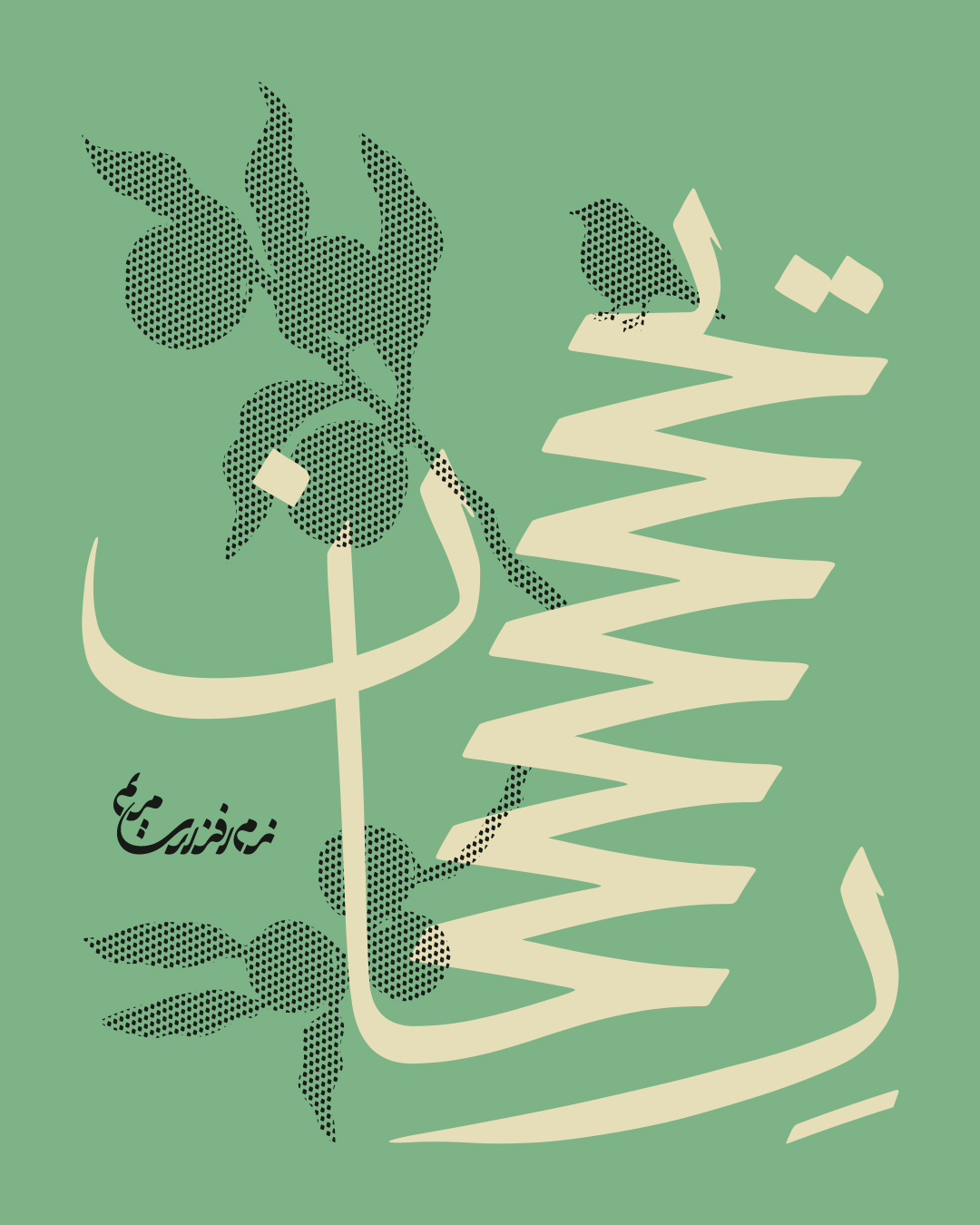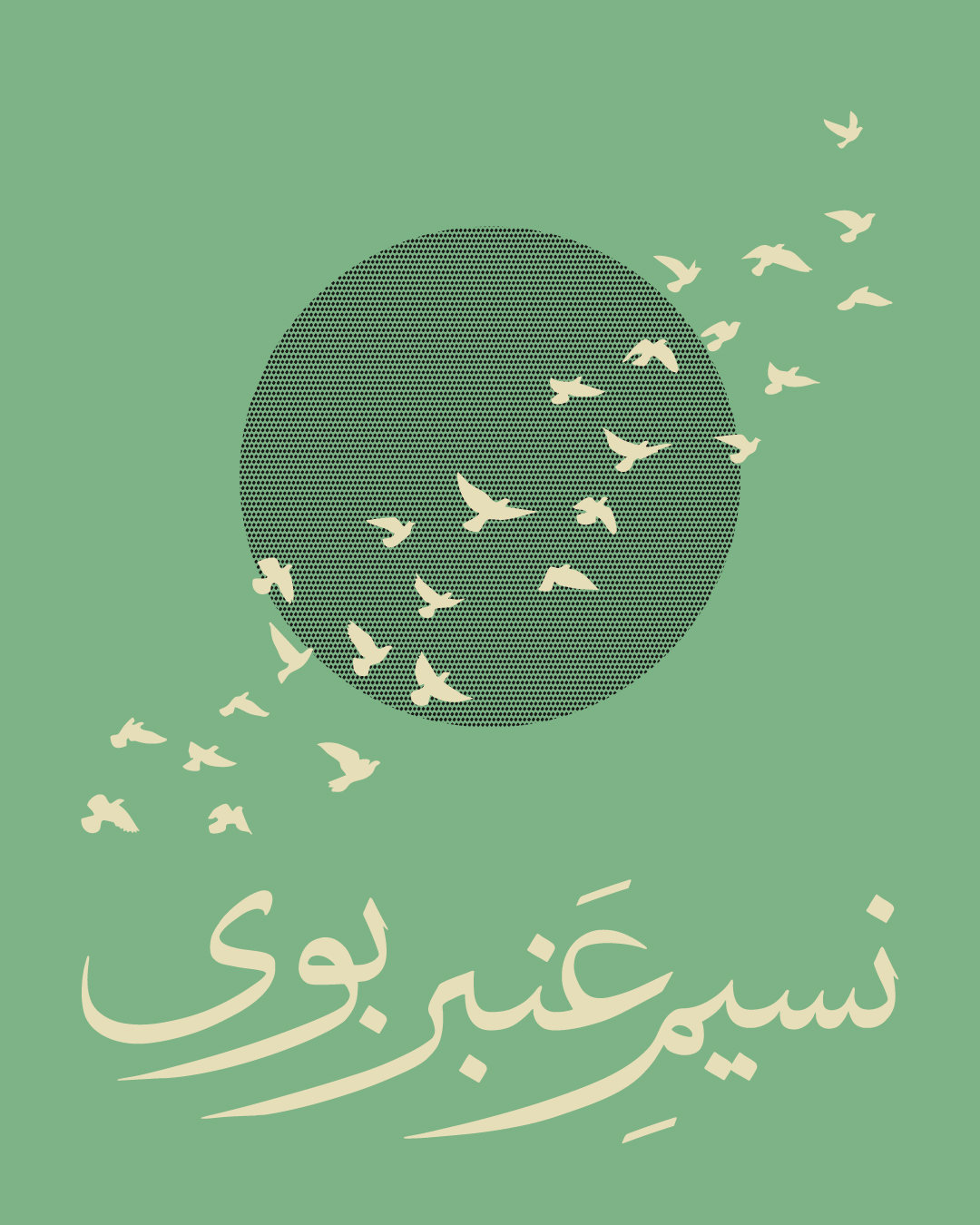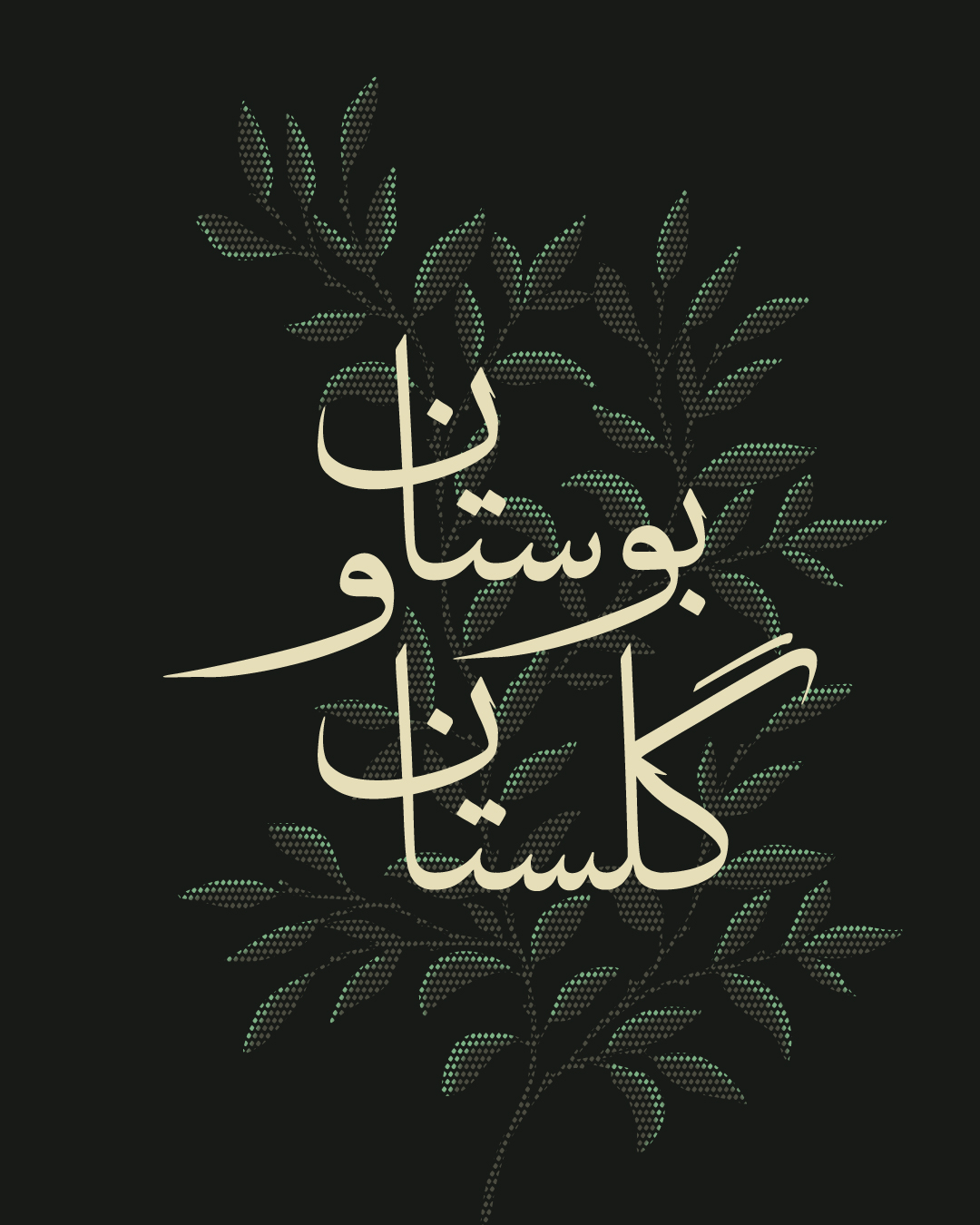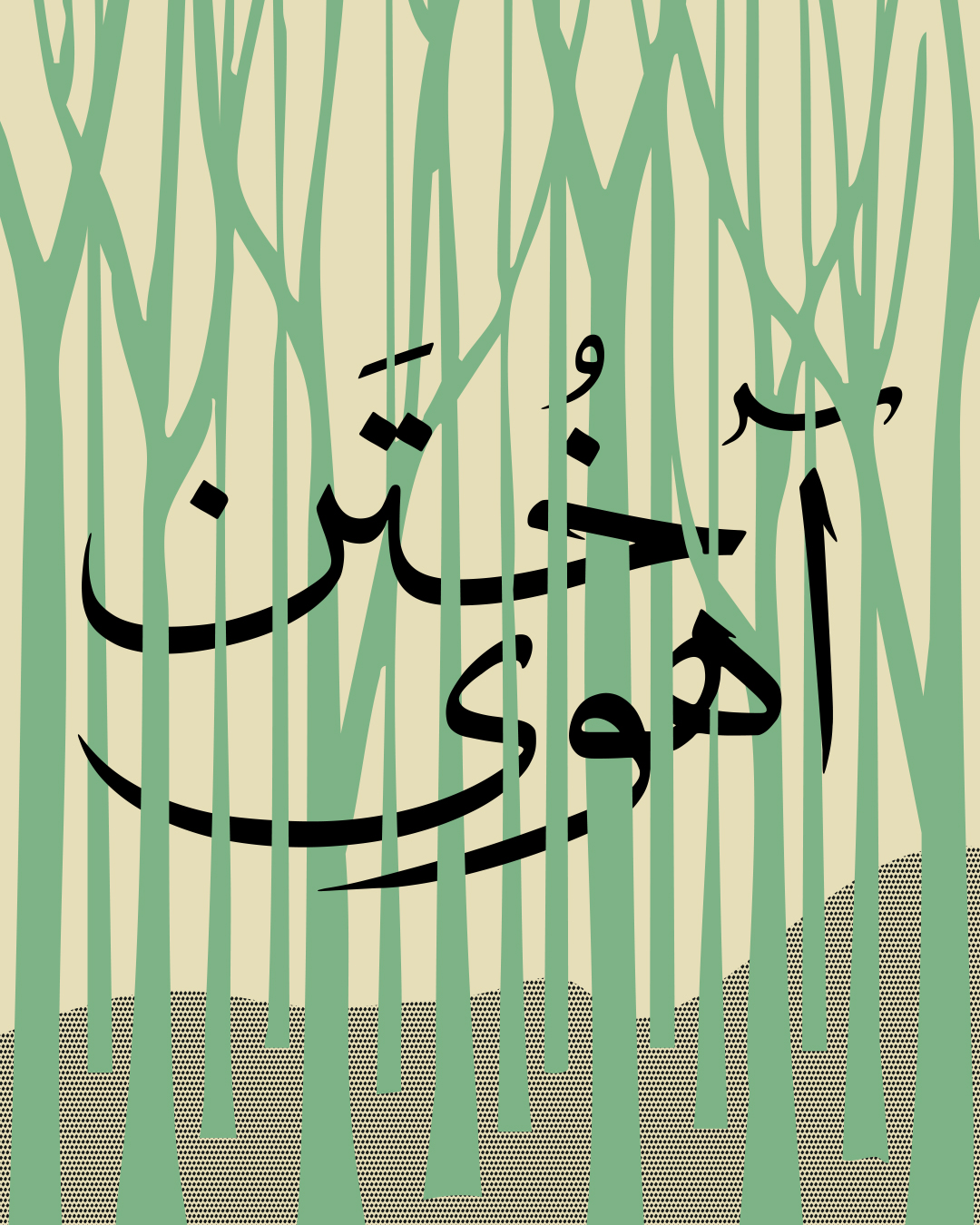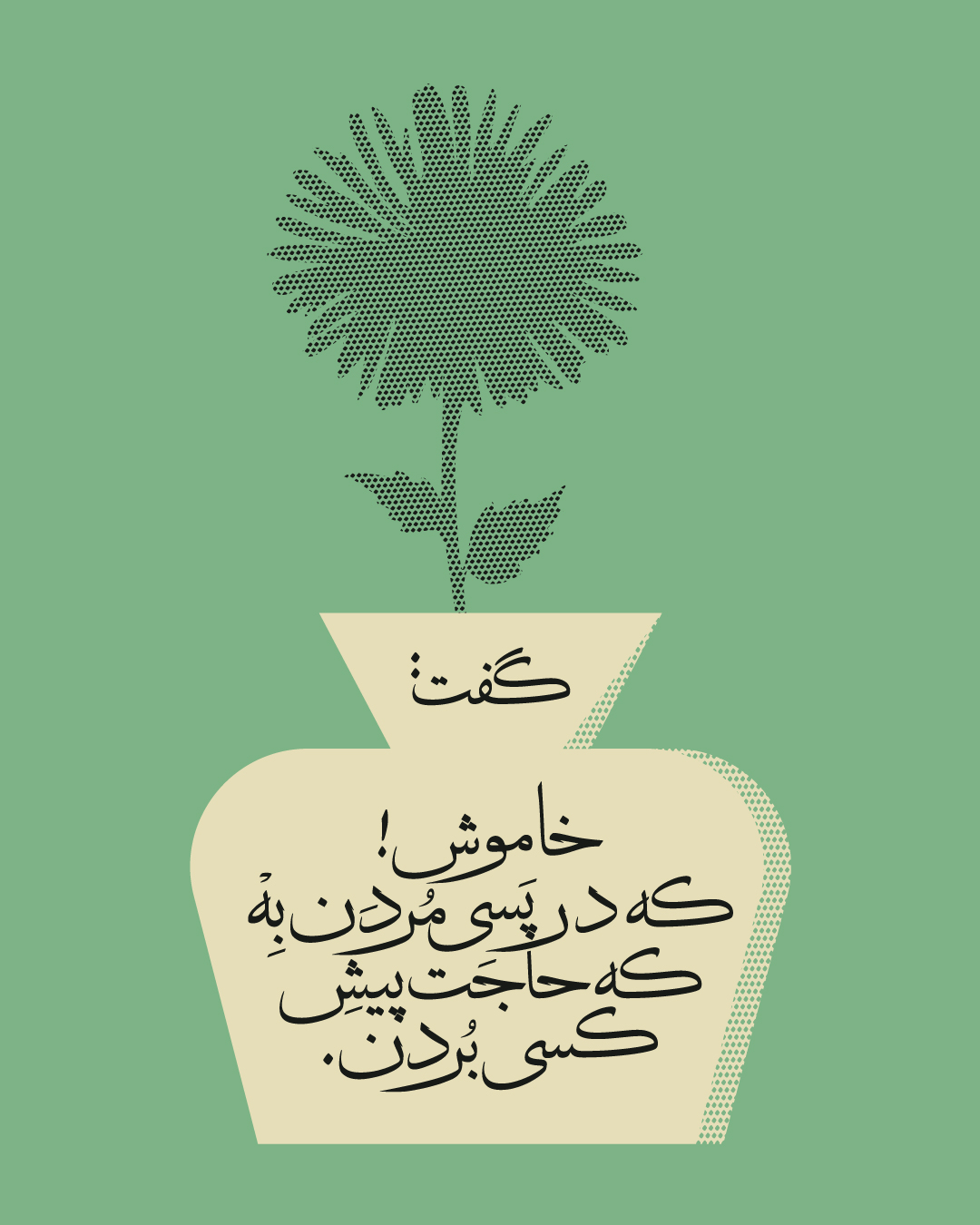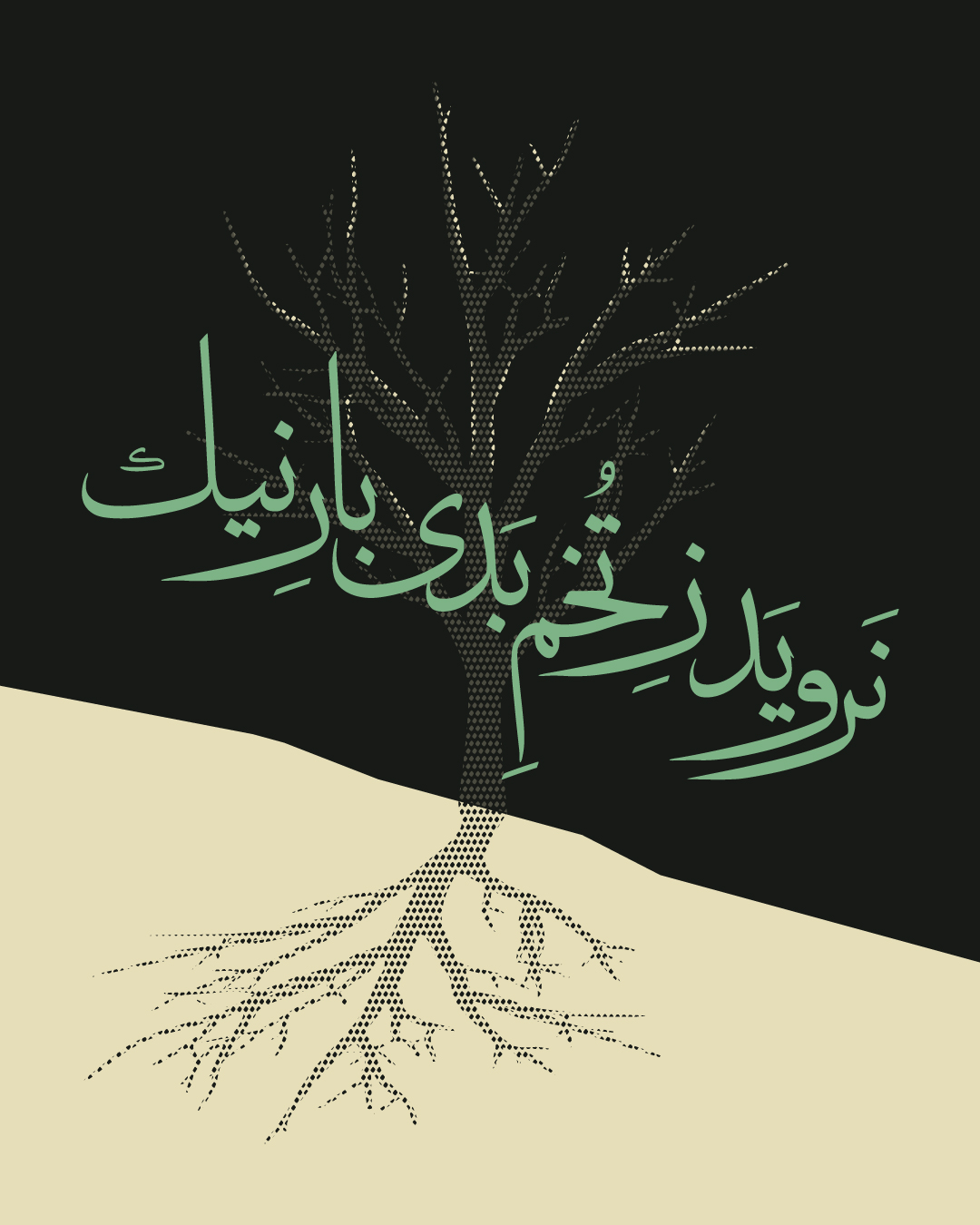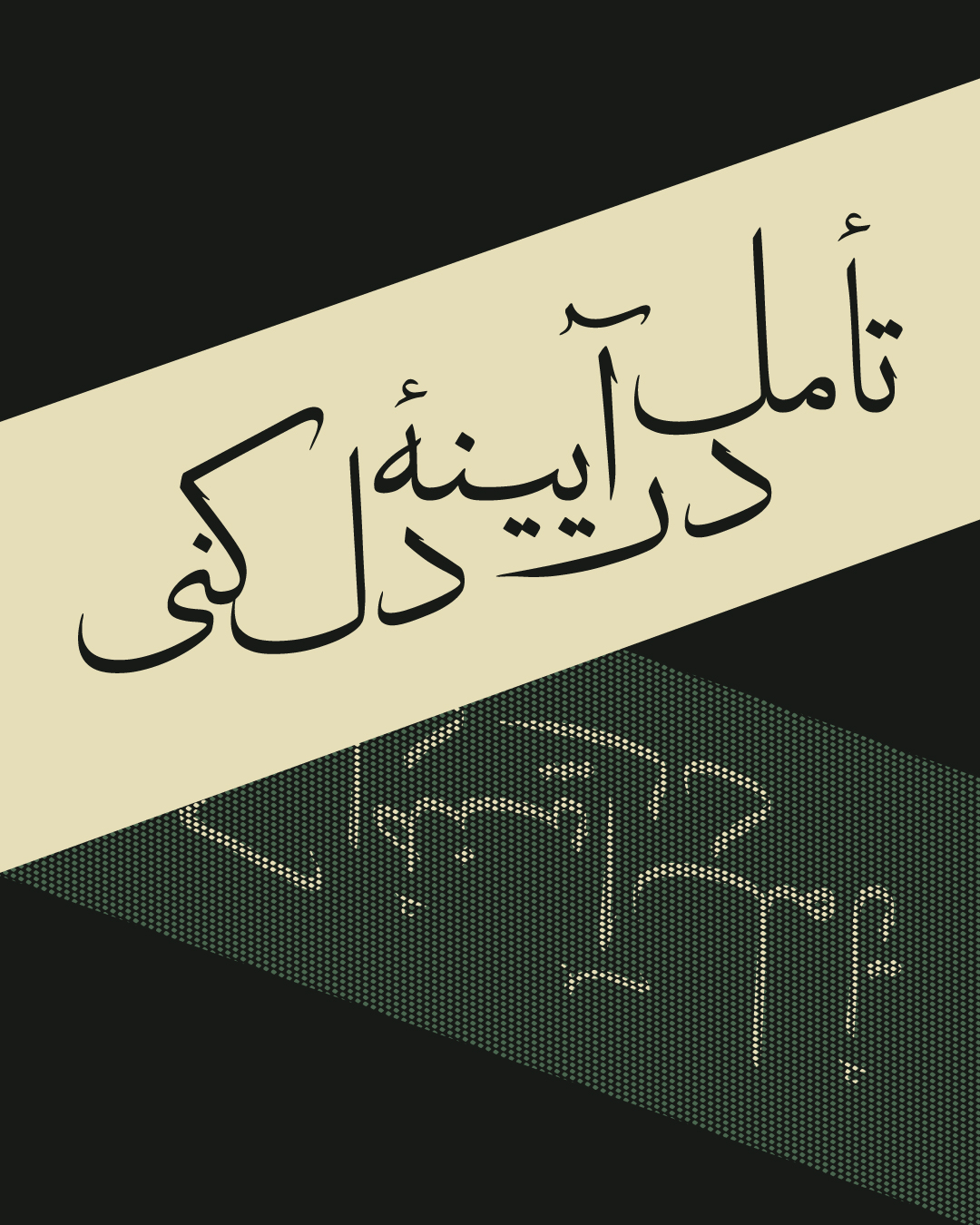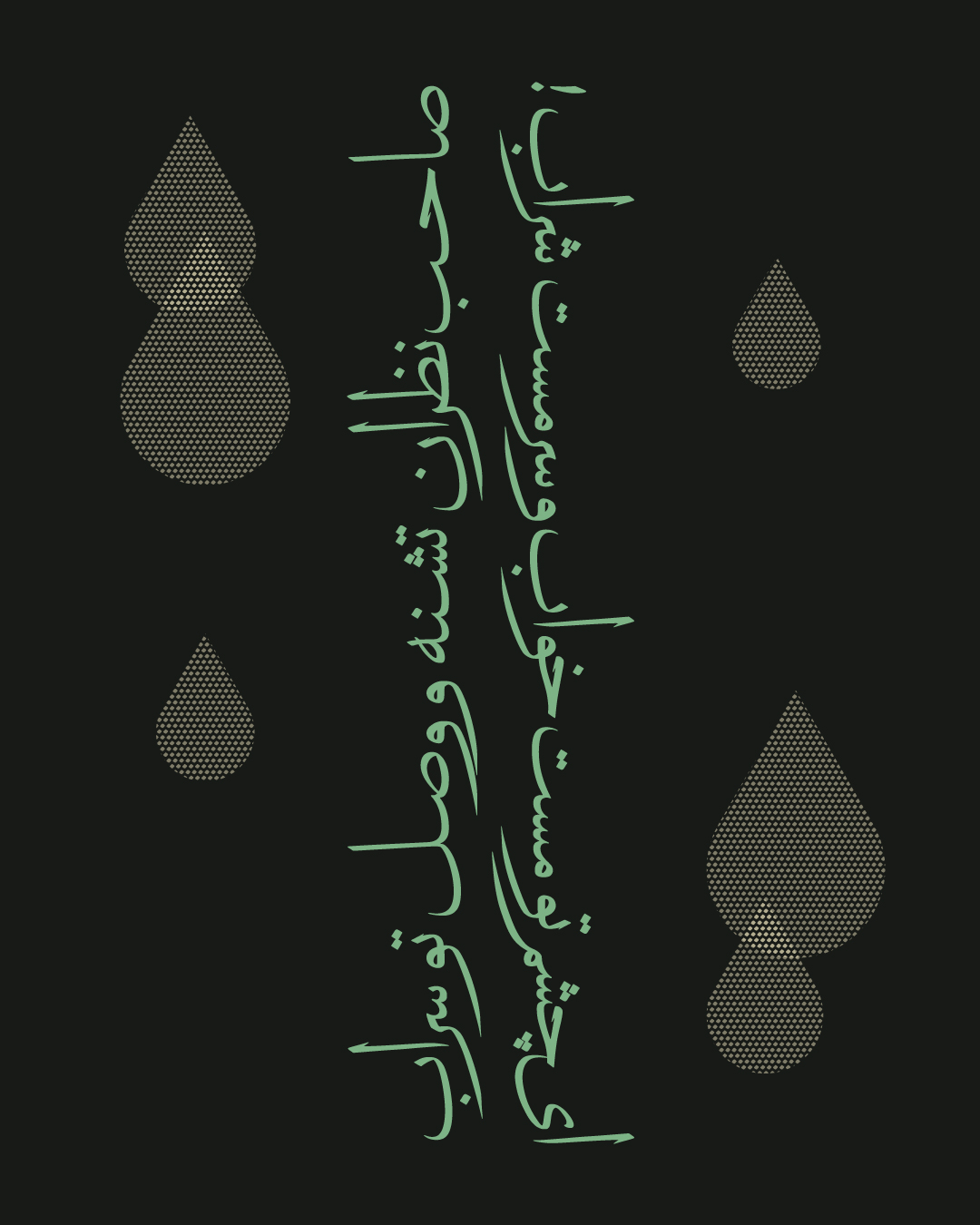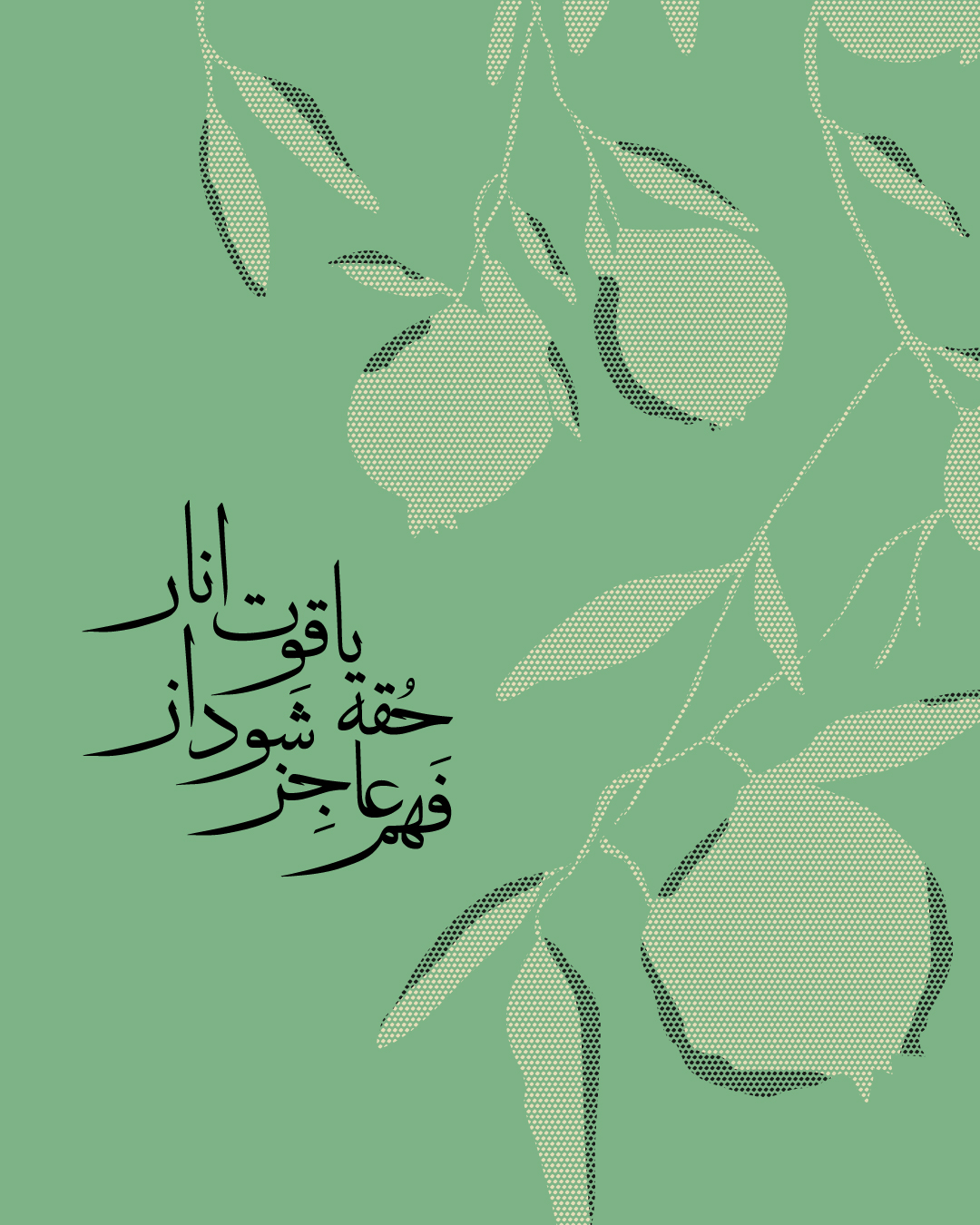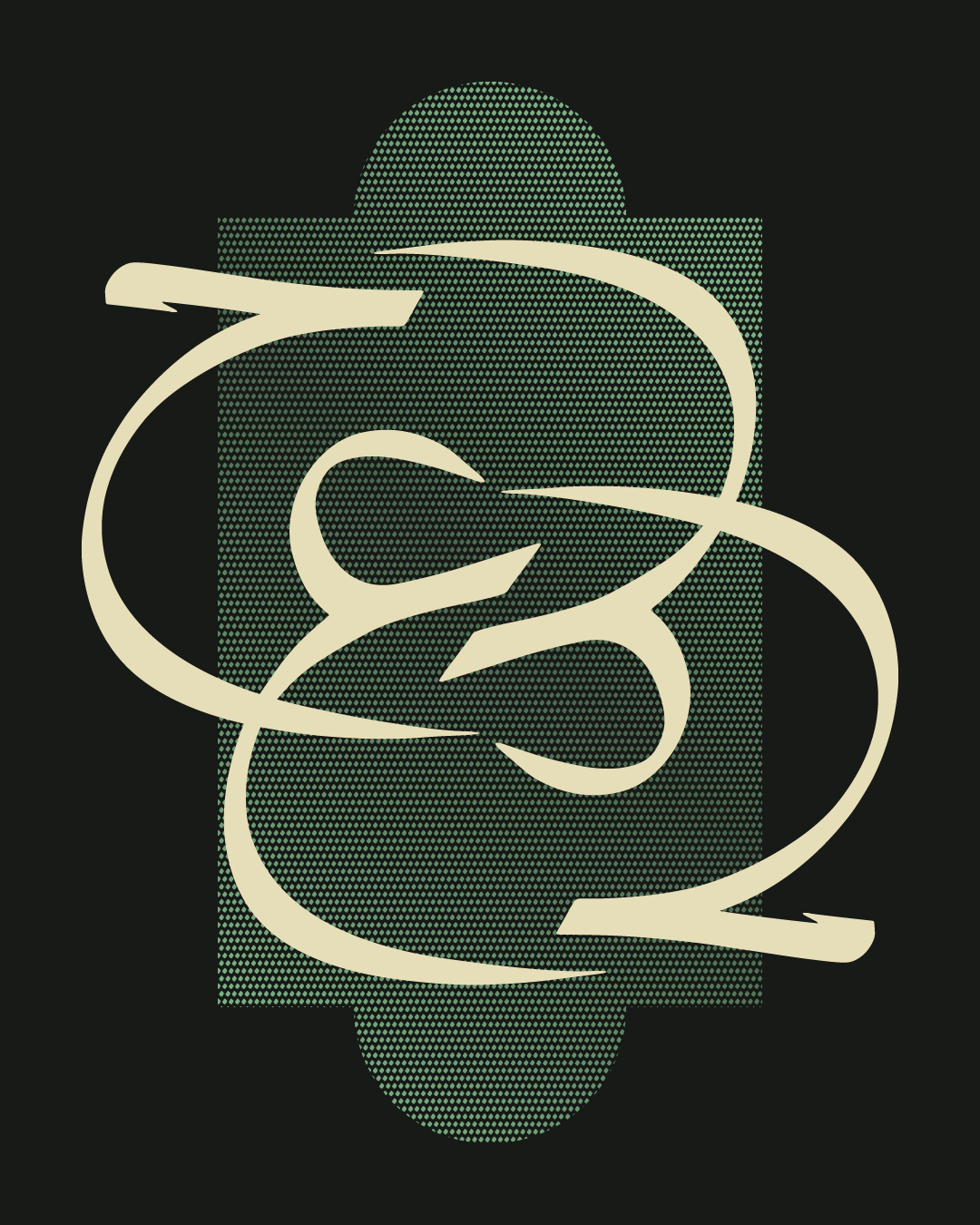
wm_Reyhan
درباره قلم ریحان
خط ریحان یکی از زیباترین خطوط خوشنویسی اسلامی است که قدمتی چندصدساله دارد. نخستین نسخه رایانهای این خط در نرمافزاری مریم توسط محمدحسن ملایمی و بر پایه قرآن چاپشده به خط ریحان ــ اثر نفیس استاد بهرام سالکی ــ ساخته شد.
نسخه اولیه در سال ۱۳۸۶ برای نرمافزار میرعماد آماده شد و پس از آن، نسخه ارتقا یافته آن در مجموعه قلم برتر ارائه گردید.
قلم ریحان دارای ترکیبها و جایگزینهای فراوان است که امکان خلق آثار متنوع و چشمنواز را به کاربر میدهد. همچنین اعرابگذاری آن بهطور کامل انجام شده تا بهویژه برای تولید آثار قرآنی و مذهبی بهکار رود.